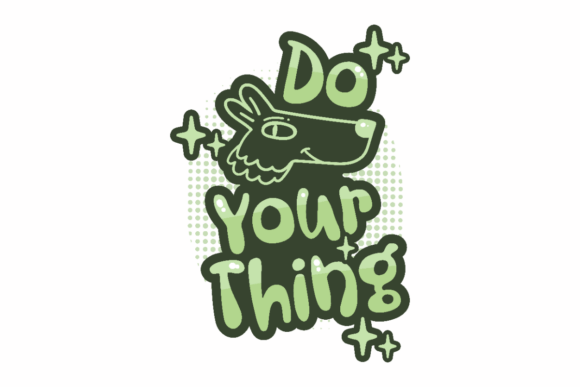
Love is Blind-Craft Lettering Font
Het vinden van de juiste ontwerpelementen kan lastig zijn, maar Love is Blind-Craft Lettering Font biedt een uitzonderlijke collectie die uw werk direct naar een hoger niveau tilt.
Of u nu POD-producten (Print on Demand), huwelijksuitnodigingen of afbeeldingen voor sociale media maakt, Love is Blind-Craft Lettering Font is een ideale keuze.